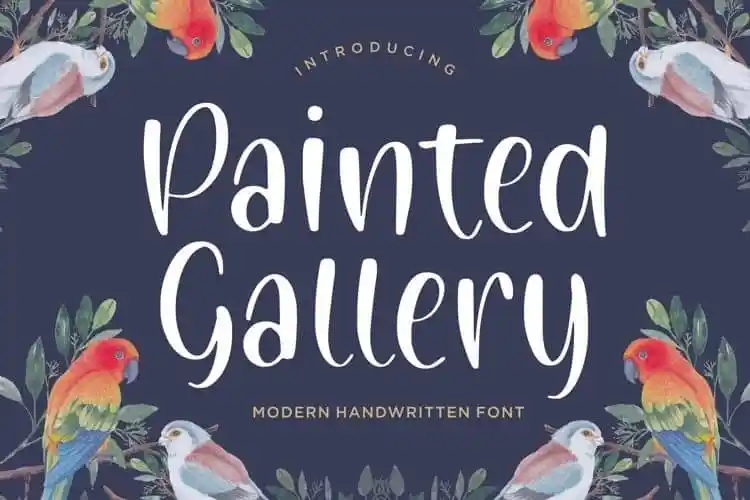
Painted Gallery Handwritten Font
A Fonte ‘Painted Gallery Handwritten’ é perfeitamente adaptada para diversos projetos digitais, tornando-a uma opção versátil para designers e produtores de conteúdo online. Suas linhas levementes e acentos naturais criam um charme único que se adapta à variedade de usos sugeridos na descrição original. A sua utilização em pacotes de produtos pode dar ao seu produto aquele toque especial, tornando-o mais chamativo e memorável para os consumidores. Para projetos de marca, a elegância da fonte combina perfeitamente com o estilo da sua identidade visual, ajudando-a a se destacar na massa de redes sociais. Em portfólios de casamentos, as linhas delicadas desta fonte têm um toque romântico que pode criar uma atmosfera quente e encantadora. Além disso, é uma opção ideal para expressar frases acima do fundo em projetos pessoais ou freelancing. Em resumo, a ‘Painted Gallery Handwritten’ se destaca como uma fonte ideal para qualquer projeto que busque um toque de personalidade e encanto.